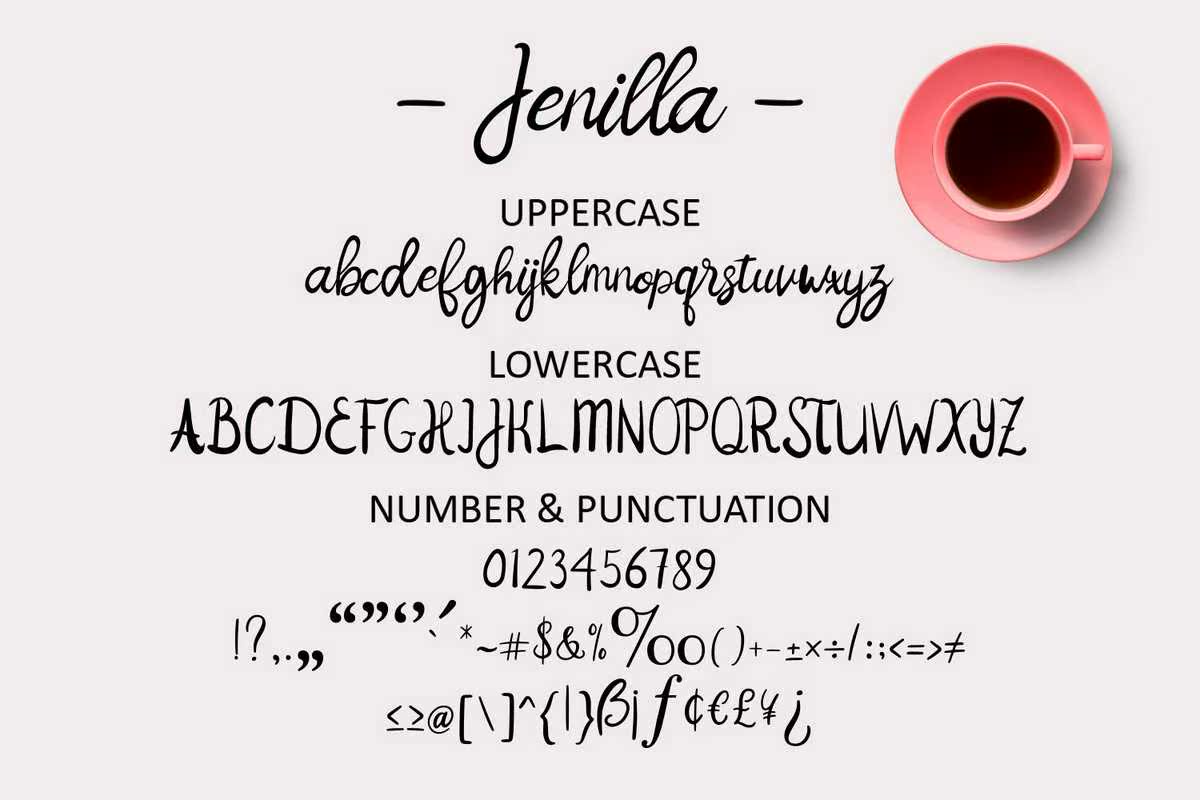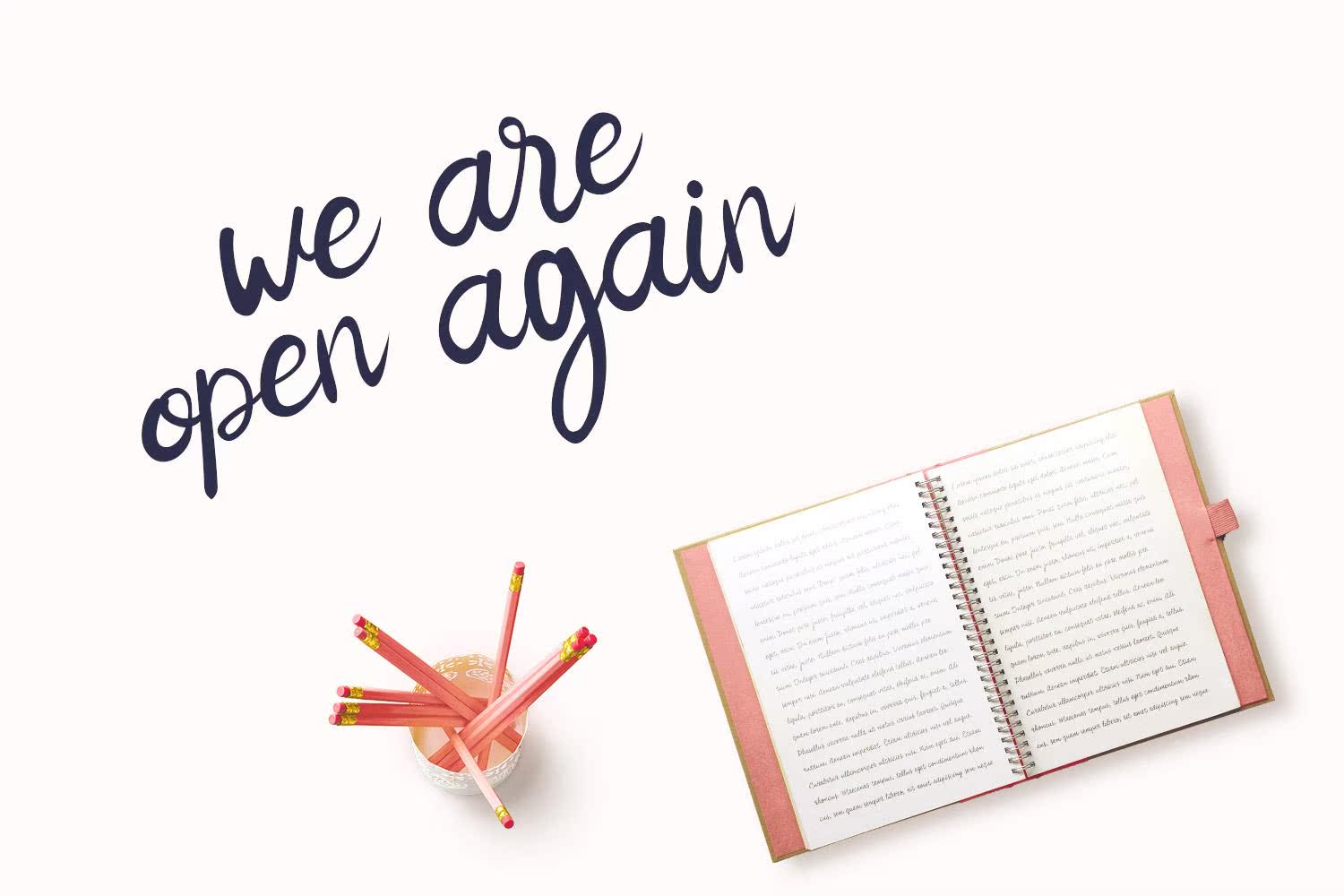
Jenilla是一款神奇的手写字体,精心制作而成,具有极高的灵活性。这是一款完美的结合了不经意间的优雅和真实的书法。它的特点是一种令人难以置信的经典风格,当我保持友谊时,我觉得向日葵是一种完美的字体,它是一种原创和持久的设计。Jenilla是一种神奇的手工字体,精心制作而成,具有如此的灵巧性。这是一种不落俗套和正宗书法的完美结合。它的特点是令人难以置信的经典风格,向日葵是形成原创和持久设计的完美元素。